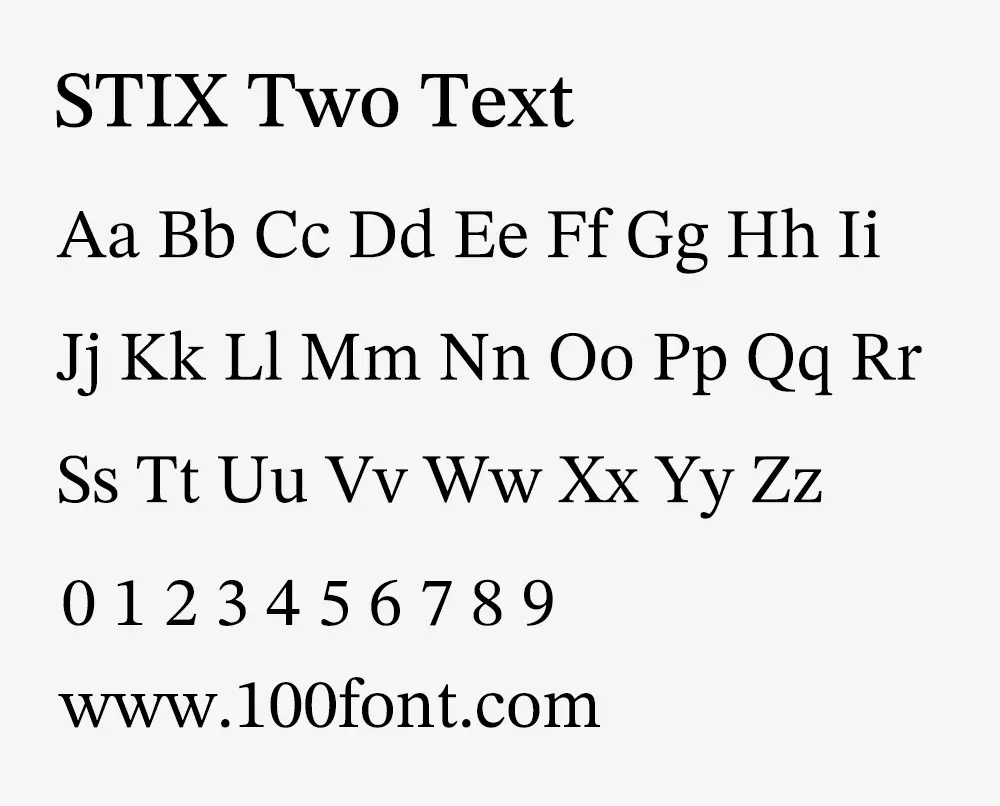
用於科學、技術和數學文本的OpenType Unicode字體
OpenType Unicode fonts for Scientific, Technical, and Mathematical texts
科技信息交換(STIX)字體旨在滿足作者、出版商、印刷商和其他從事科學、醫學和技術領域工作的人的苛刻需求。他們將基於Unicode的數學符號和字母集與一組適合專業出版的文本面相結合。根據SIL開放字體許可證,這些字體是免費的。
The Scientific and Technical Information eXchange (STIX) fonts are intended to satisfy the demanding needs of authors, publishers, printers, and others working in the scientific, medical, and technical fields. They combine a comprehensive Unicode-based collection of mathematical symbols and alphabets with a set of text faces suitable for professional publishing. The fonts are available royalty-free under the SIL Open Font License.